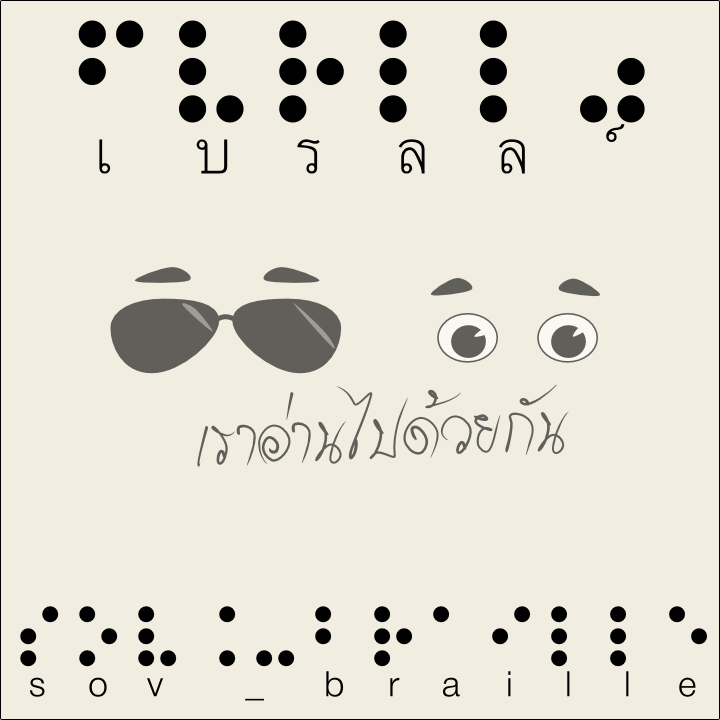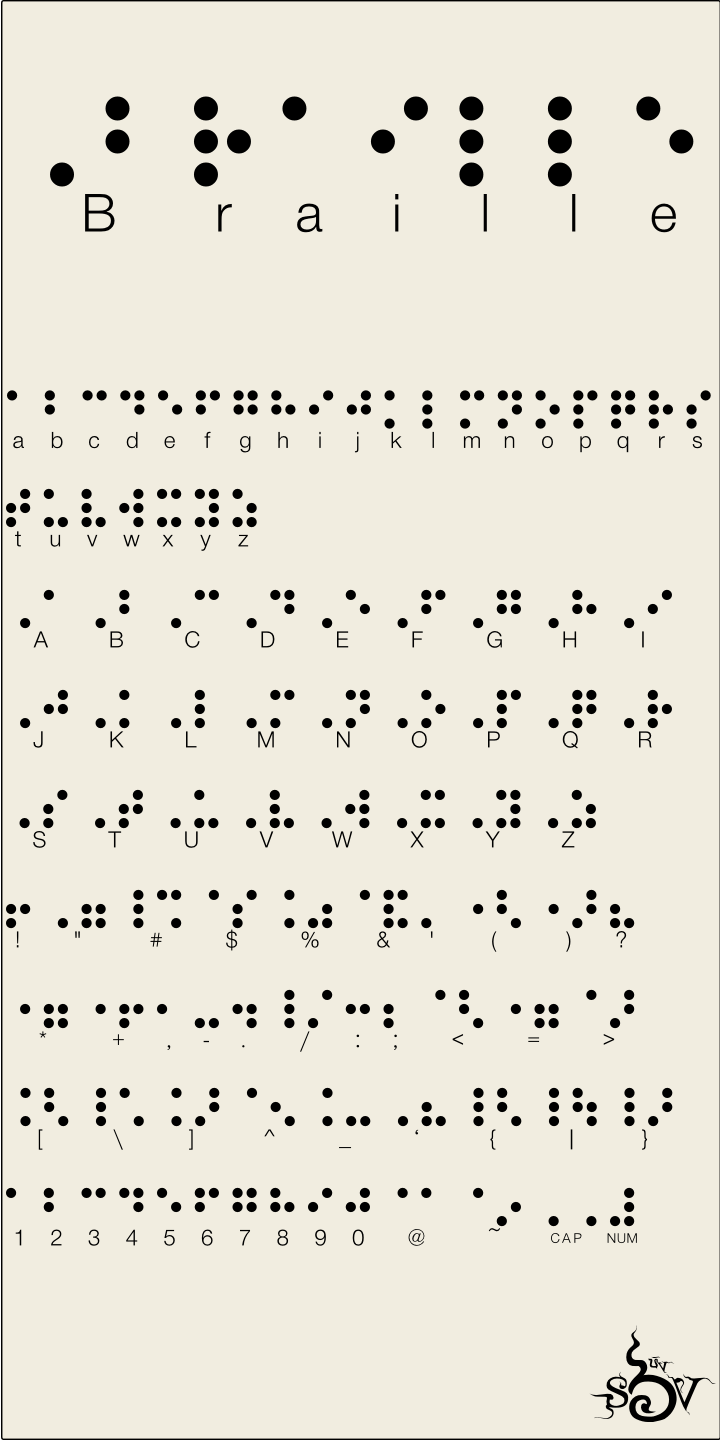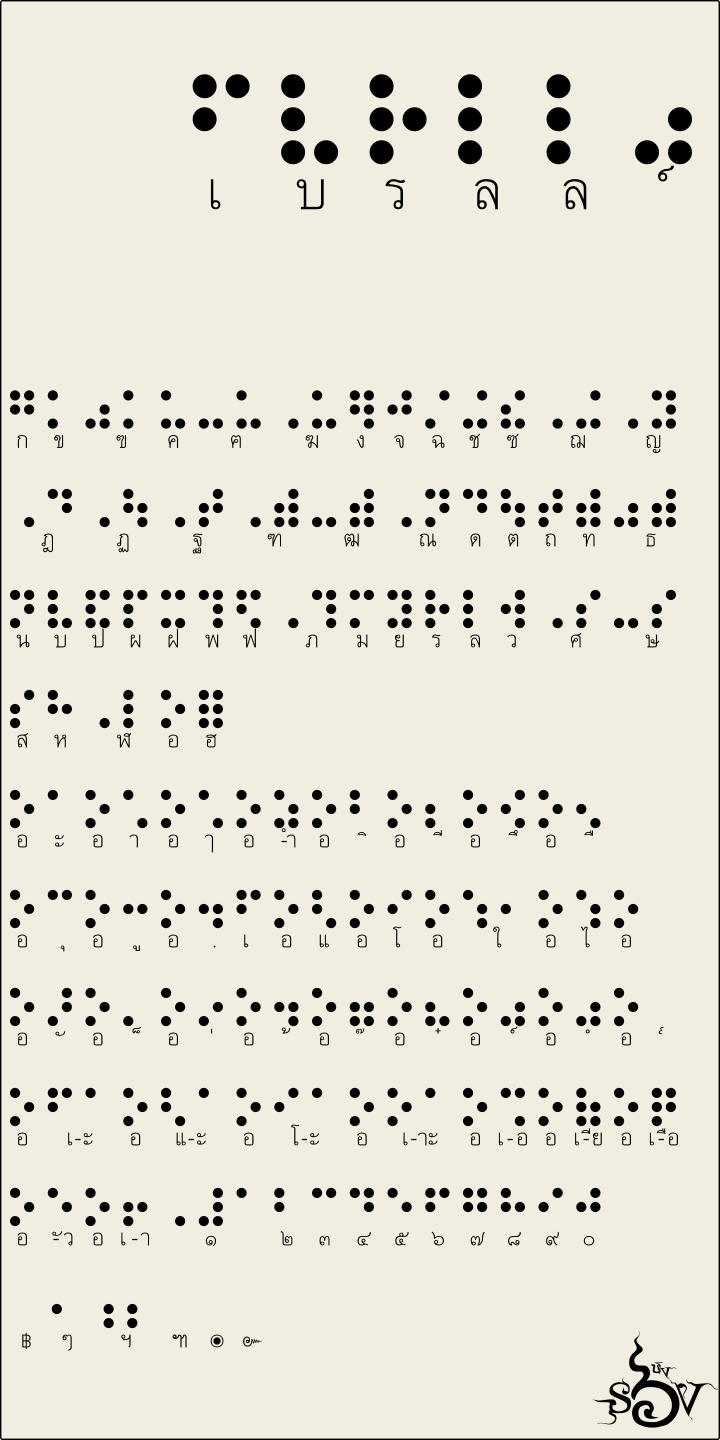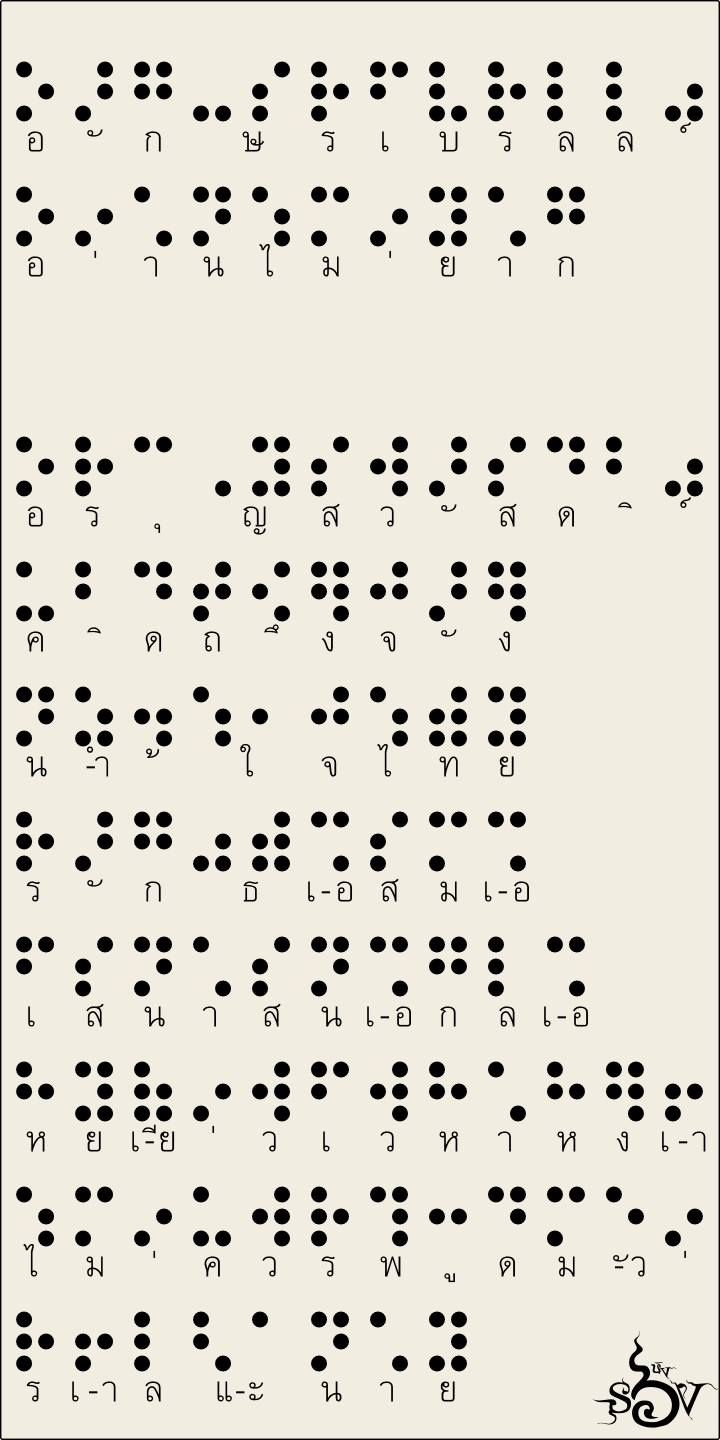
เบรลล์ (SOV_Braille)
หลังจากได้มีโอกาสไปทำจิตอาสาที่โรงเรียนสอนคนตาบอด พบว่าอุปสรรคอย่างหนึ่งคือพวกเราไม่มีความรู้เกี่ยวกับอักษรเบรลล์เลย ทำให้การช่วยเหลือผู้พิการทางสายตาถูกจำกัด เพราะความไม่รู้ จะดีหรือไม่ถ้าเรามี ฟอนต์ที่อ่านได้ทั้งคนตาปรกติ และคนอ่านเบรลล์ได้ โลกสองใบจะได้เชื่อมกันง่ายขึ้น
สิ่งที่จะทำให้สมบูรณ์สำหรับฟอนต์นี้ คือการนำตัวจุดกลมไปพิมพ์นูน เพื่อให้ผู้บกพร่องทางสายตา ส่วนตัวอักษรปรกติไม่ต้องนูนก็ได้ครับ